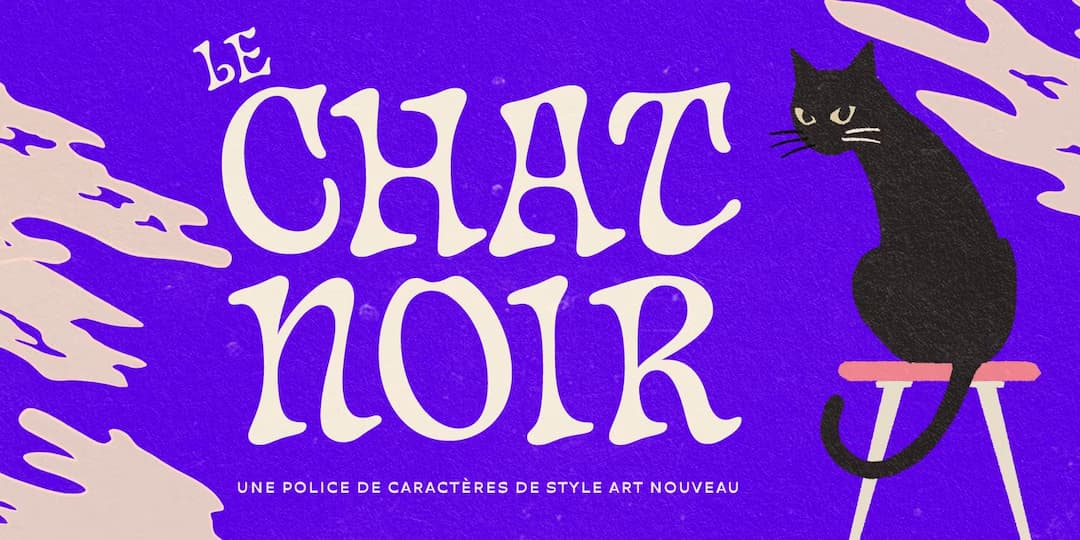
Chat Noir
筆で書いたようなニュアンスが残るアール・ヌーヴォー風味のディスプレイ。カリグラフィーの技術を用いて書かれたようななんとも不思議な書体で、骨格はほぼ垂直ではあるが、セリフなどのエレメントのせいで全体的に左に傾いて見えるのも面白い。アウトラインはぬたっとして粘り気を感じる。大文字のみの書体ではあるがオルタネートが結構あって、退屈せずに楽しめるだろう。名前はフランス語で黒猫の意。1ウェイト。